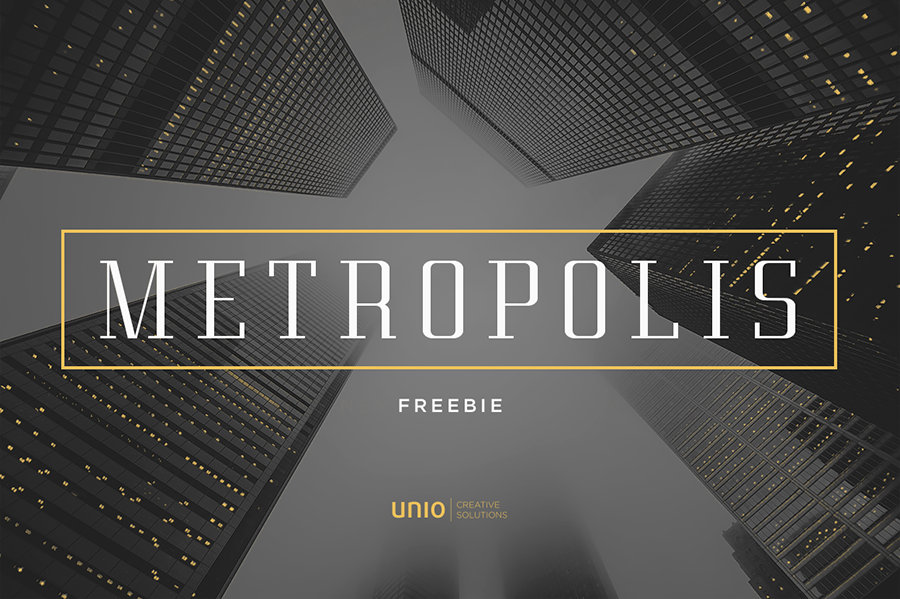
Metropolis Font – Fonte Grátis
Metropolis Font
Metropolis Font é uma elegante tipografia serif que captura a essência do contraste entre a cidade clássica e moderna. Suas linhas delicadas e curvas suaves permitem que estejam perfeitamente adaptados tanto para leitura de exibição quanto como headlines, ou mesmo corpo do texto, proporcionando um acabamento sofisticado sem sacrificar legibilidade. Ideal para designers buscando uma tipografia que se conecta intimamente com o espírito urbano, Metropolis oferece uma solução versátil que pode tornar qualquer projeto mais profissional e atrativo. Seja para empregos onde a leitura é crucial ou quando desejas um toque de elegância em seu design gráfico, esta fonte será uma escolha acertada. Com sua sofisticação única e seu poder de adaptação versátil, Metropolis oferece um recurso valioso para qualquer designer comprometido com a qualidade do seu trabalho.